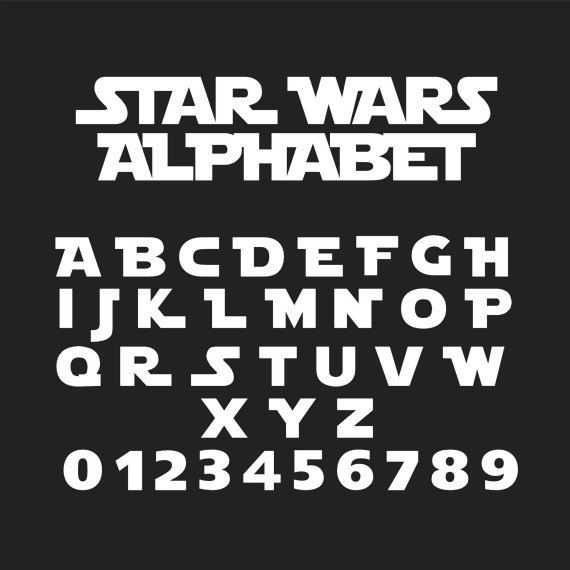
18 бесплатных шрифтов Звездных войн
Шрифт Звездных войн
«Звездные войны» — американская эпическая медиа-франшиза о космической опере, созданная Джорджем Лукасом, которая началась с одноименного фильма 1977 года и быстро стала
.Звездный джедай шрифт бесплатно
Star Jedi — это высококачественный научно-фантастический шрифт, разработанный Boba Fonts и доступный для бесплатной загрузки в личных и коммерческих целях.
Мандалорский шрифт
Mandalorian — это высококачественный шрифт Disney, разработанный Erikstormtrooper и доступный для бесплатной загрузки в личных и коммерческих целях. Бесплатная версия
Шрифт Blueprint77
Blueprint77 — это высококачественный шрифт Disney, разработанный Corvus 113, который доступен для бесплатной загрузки и личного использования. Бесплатная версия
Ручной шрифт Аурек-Беш
Aurek-Besh Hand — это высококачественный шрифт Disney, разработанный Boba Fonts и доступный для бесплатной загрузки в личных и коммерческих целях.
Шрифт Shadow of Xizor
Shadow of Xizor — это высококачественный шрифт Disney, разработанный Boba Fonts и доступный для бесплатной загрузки в личных и коммерческих целях.